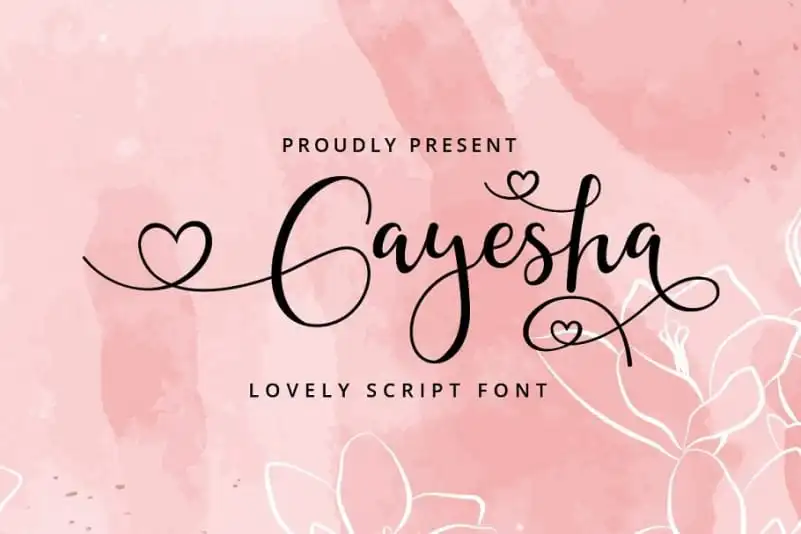
A Gayesha Calligraphy Font é uma opção única para designers buscando adicionar uma personalidade encantadora a seus projetos. Com traços fluidos e alternativas incríveis, esta fonte é perfeita para quem busca algo romântico e feminino. Ela traz um toque delicado e giratório aos seus trabalhos de texto, tornando-a uma escolha ideal para aplicativos como logotipos, capas de livros, posters, embalagens de produtos e até cartões de felicitações. A fonte suporta múltiplas línguas, tornando-a versátil e adaptável a diversos formatos de projeto. Embora seja uma tipografia script mais leve e giratória do que muitas outras disponíveis, a Gayesha mantém um grau elevado de precisão. Suas alternativas sofisticadas oferecem um leque amplo de opções para criar texturas variadas e interessantes sem perder a elegância da fonte principal. O open type presente no design permite ajustar os espaçamentos entre linhas, o que torna ainda mais personalizável seu uso na criação de letras. Para quem busca expressar um toque delicado e feminino em seus projetos visuais, a Gayesha Calligraphy Font é uma escolha inteligente. Suas alternativas abrangentes garantem que você possa alcançar o máximo de criatividade sem comprometer a legibilidade ou estilo elegante da fonte.